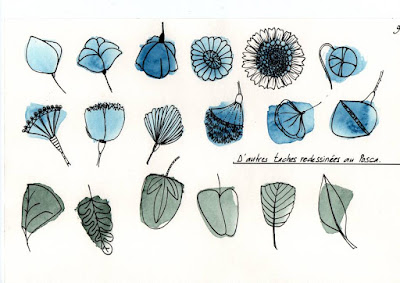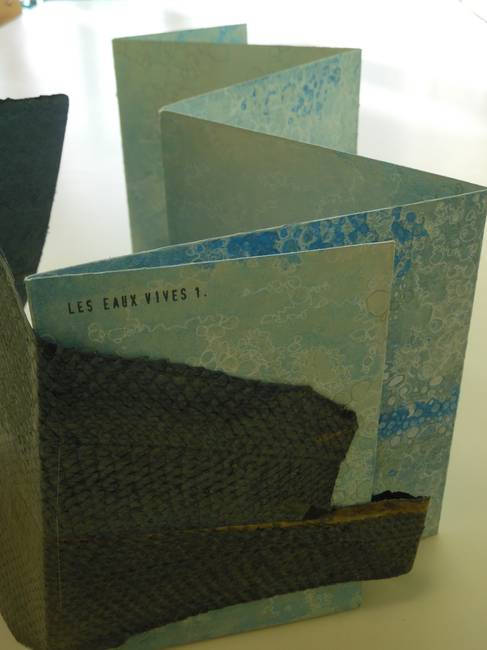
Zomerstage Scriptores 2018
Scriptores est une association de calligraphie latine européenne qui compte des membres en Belgique et aux Pays-Bas. Elle organise chaque année en été trois stages de 6 jours en parallèle.
Pour l'été 2018, du 29 juillet au 4 août, Scriptores a sollicité trois calligraphes pour animer ces stages : Baukje SCHEPPINK, Rachel YALLOP et moi-même.
Le thème du stage que je propose est : "Matière, composition & Calligraphie sur Mdf ",
Les eaux vives 1.
Voici le premier livre d'une série de cinq : "Les eaux vives". Ils prendront tous la forme d'un leporello 15x15 cm replié, protégés par une couverture en cuir de poisson.
Le titre explicite le contenu graphique : l'eau bouillonnante, pétillante, effervescente, oxygénée, métaphore d'une énergie vitale.
Papier aquarelle enduit, pigment, pointe d'argent, stylo gel, tampon composable, cuir de saumon.
Demain à l'aube..... à l'antre temps
En janvier et février prochains, j'expose dans la galerie rennaise de Constance Villeroy "l'antre temps" en compagnie de Patricia Chemin.
Je présenterai une sélection d'Autres lieux, quelques espaces subjectifs et des réalisations récentes : les "Grammaires blanches", "Brut"et des "Silver point".
Cette année encore, je participe au Salon du livre et ses métiers d'art, je serai présente à Montreuil-Bellay le samedi 24 et le dimanche 25 dans le Prieuré des Nobis pour la quatrième édition du salon. J'animerai ensuite un stage de trois jours sur le thème "Matière & composition sur papier enduit". Au programme, un éventail de techniques sur carrés 15x15 resserrés dans un étui plié et un petit livre accordéon avec une couverture cousue à fenêtre..... un espace pour mettre en espace et en rythme des textures, et pourquoi pas des signes graphiques, des trames calligraphiées ou des parterres de fleurs stylisées.....
Donc je résume : expo et stage en février ..... mais ce n'est pas fini, je continue : au printemps je reviendrai deux fois dans la belle cité blanche, une première fois en compagnie de Jean-Noël Riou pour un stage CO.RI et une deuxième fois seule pour un stage de gestuelle au colapen....
Stage CORI : Work in progress
C'est le deuxième week-end CORI en décembre et c'est donc Jean-Noël Riou qui initie les stagiaires aux ficelles de la perspective, à la règle du gras sur maigre, à la pose des glacis, à la construction d'un volume avec des ombres et de la lumière....
Là, c'est l'exercice des galets, en cours d'exécution, il reste à poser les lumières et assombrir les sombres sans utiliser le noir.....
Retour de Véronique Gaudiot sur le stage "Des lettres et des fleurs"
| Brainstorming-Flowers par Véronique Gaudiot |
Elle analyse le processus de création que Marine nous a fait mettre en œuvre, y ajoute des éléments d'expérience personnelle et une réflexion sur la créativité. Passionnant. Et bonus, elle nous propose une piste de travail : "Les 100 fleurs". Elle me donne bien envie de relever le défi. Je pense que chacun(e) souhaitant développer un répertoire de formes - en calligraphie gestuelle par exemple au hasard - gagnerait à appliquer cette méthode.
| Une partie de mes "100 fleurs" |
Toujours avec Marine PSM : des fleurs et puis des lettres...et des chiffres
Le deuxième jour du stage "Lettres et fleurs de Marine Porte de Sainte-Marie a passé trop vite. Nous avons continué à dessiner des fleurs stylisées et nous y avons associé des lettres. J'avais préparé une série de papiers enduits colorés blanchis et je les ai utilisés comme support à de petites compositions mariant lettres dessinées et fleurs graphiques dans un esprit design d'intérieur.
Marine nous avait laissées libres de dessiner les lettres dans un esprit typo ou de les calligraphier.
| des chiffres |
&
| des lettres |
Lors du stage j'ai rencontré en "vrai" Véronique Gaudiot avec laquelle j'échange de belles lettres en janvier. Elle pratique avec bonheur le lettering, mêlant lettres vintage et illustrations au trait.
Elle nous a montré un album de réalisations pendant le stage :